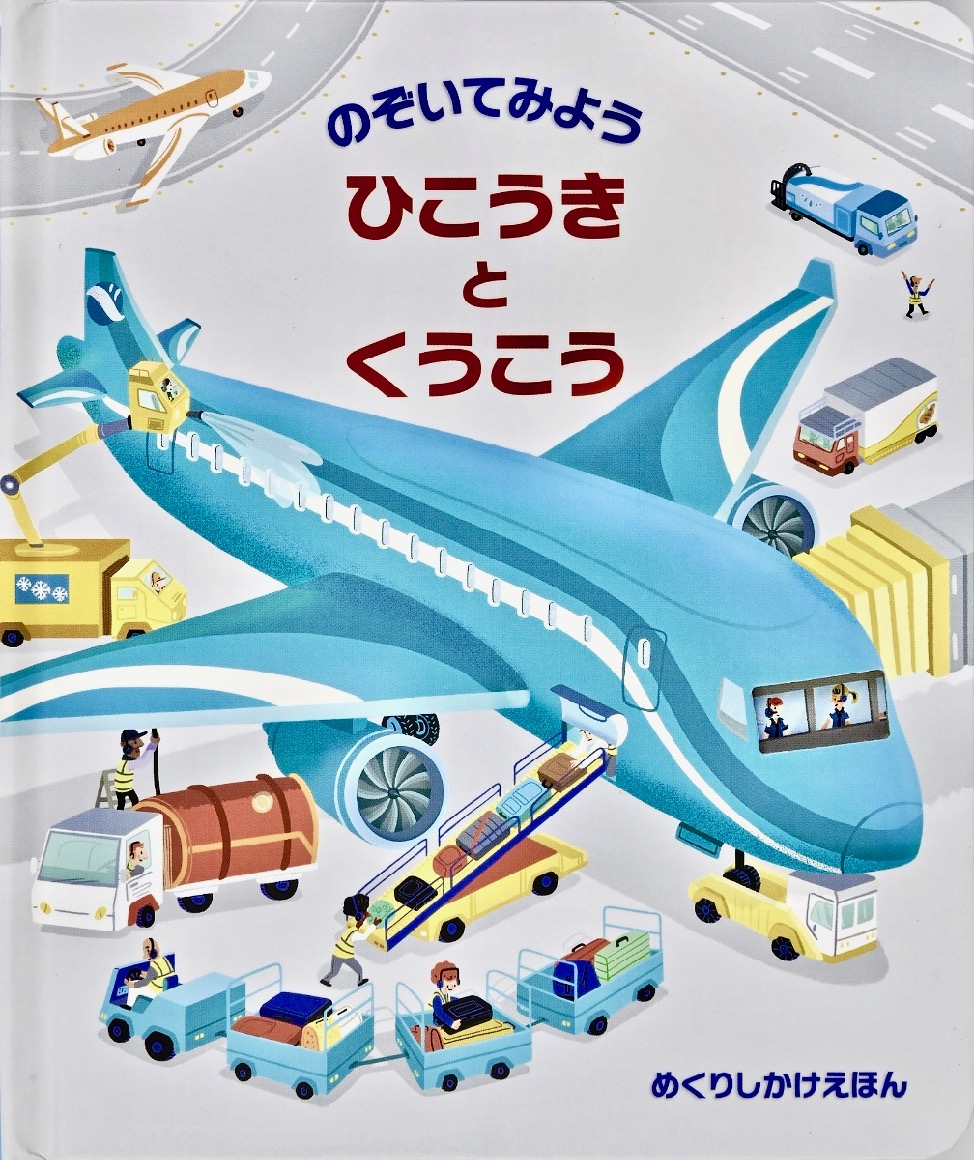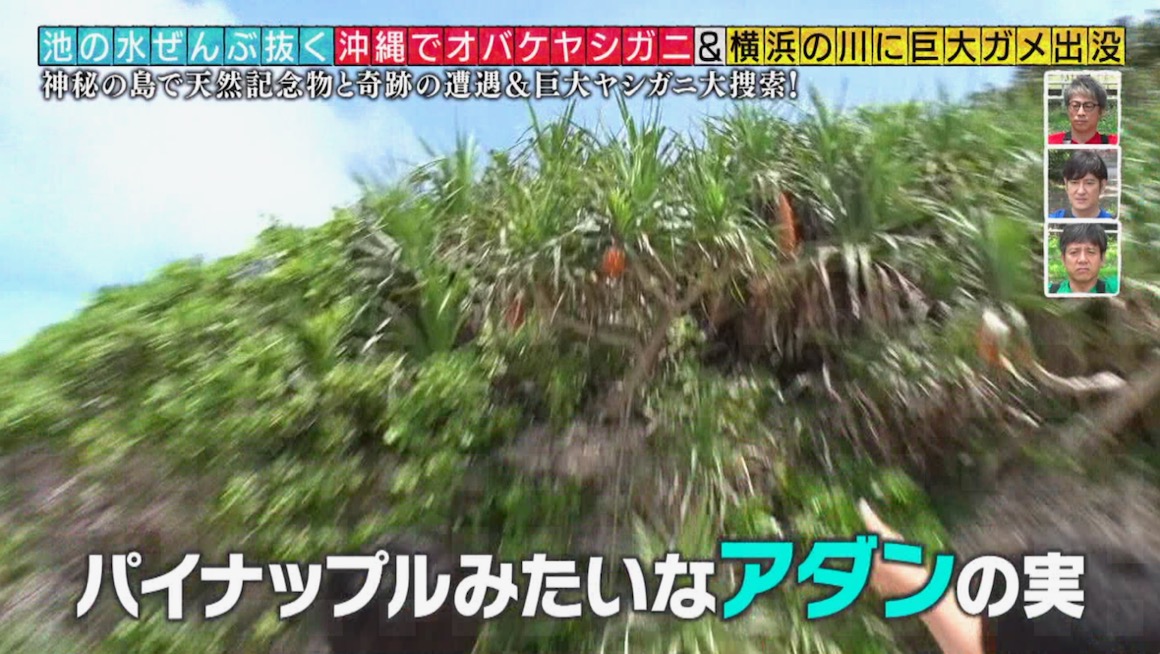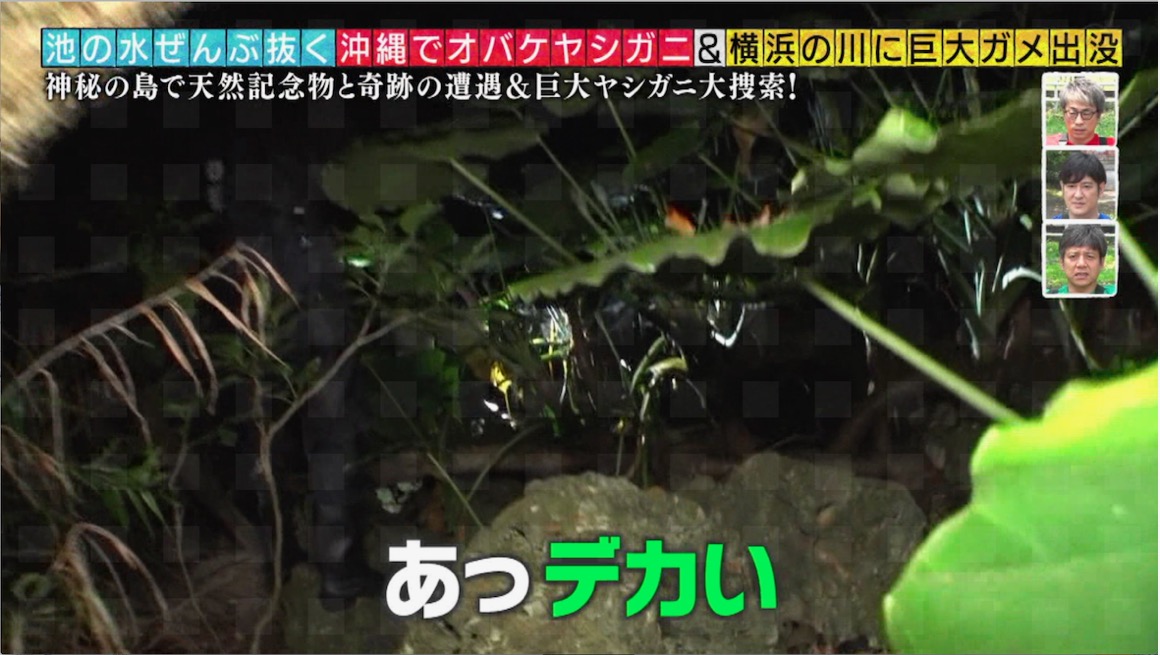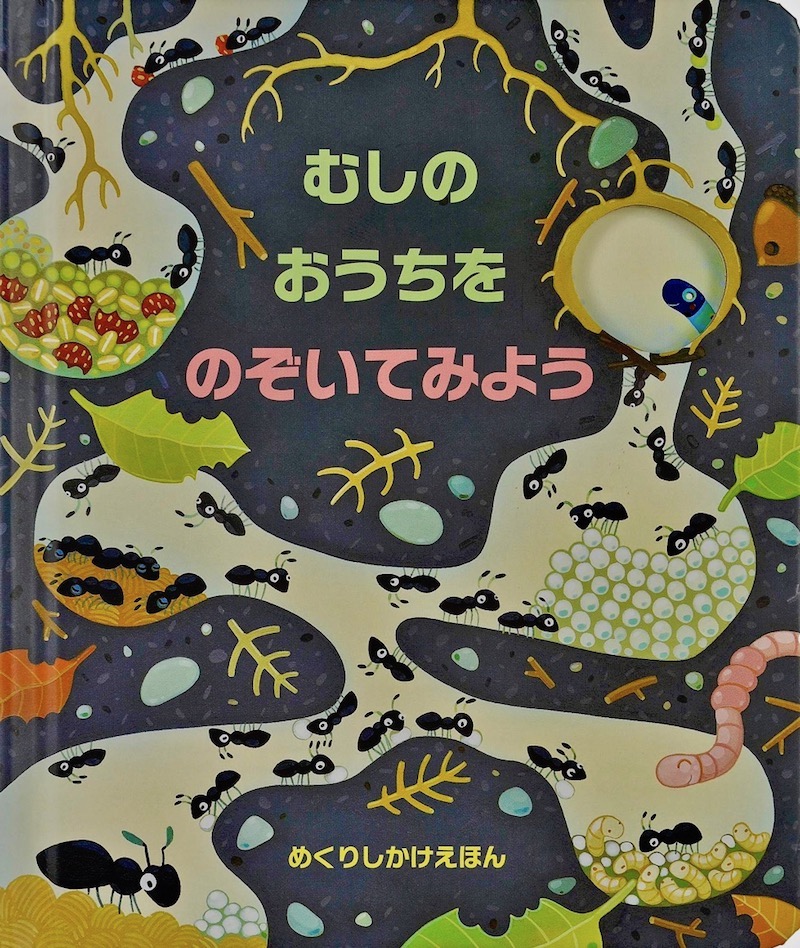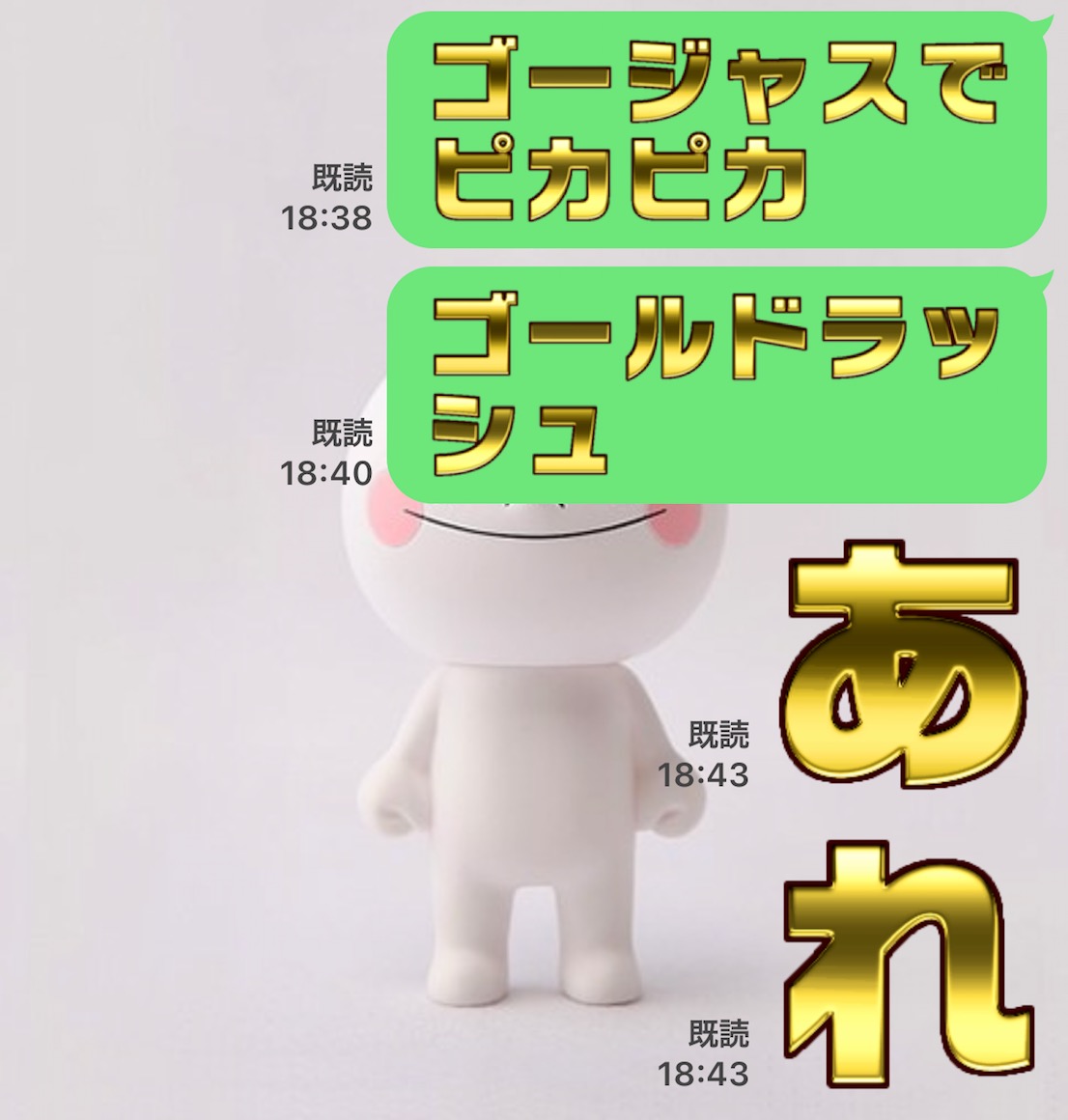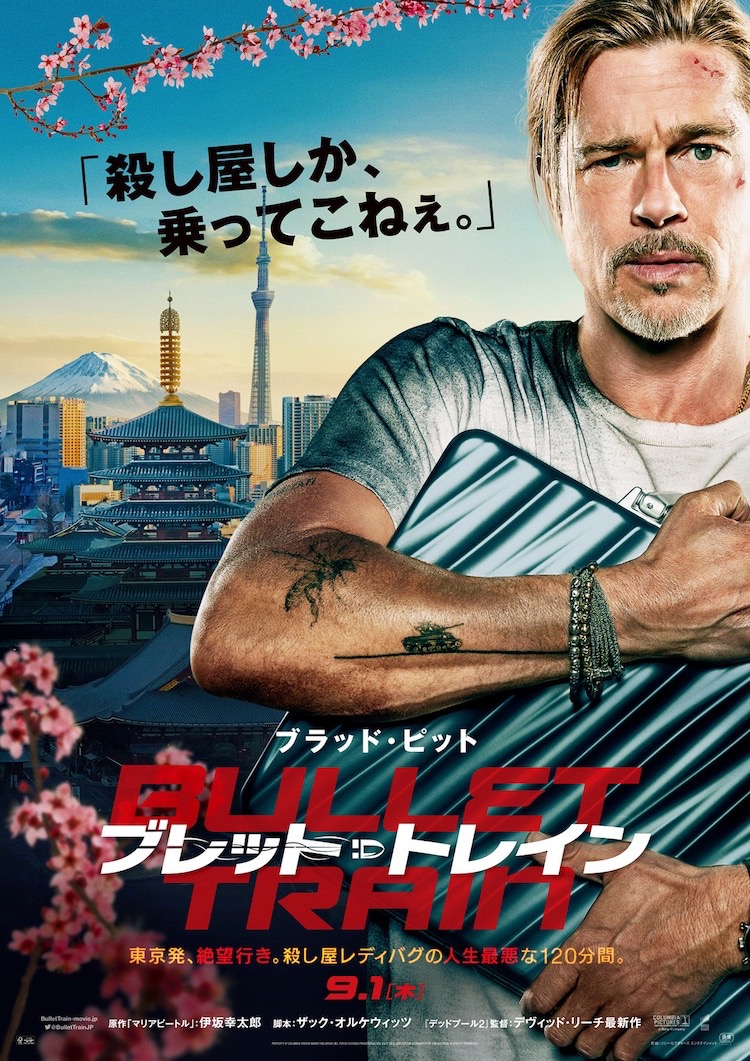
マクドナルドの求人広告画像。
もうひとつ。
チキンタツタとおろしチキンタツタ。
商品パッケージ。
花王株式会社は、お客さまが365日24時間いつでも自分らしく、ごきげんで過ごせる社会を目指し「#ごきげんをつくろう」と称した活動を昨年秋より進めています。
文字色のグラデーションがキレイ…。
まだある。
もうひとつ。
大谷くんが出場する試合は、よく観てる。
こんなのも…。
日本テレビ 世界まる見え!テレビ特捜部
これも…。
まだある。
もうひとつ。
今日から大阪で始まった展覧会、アシタノタイポ展。
サトウY氏の出品作品には、私の書体が使われている。
これがサトウY氏の作品かな。
こんな「ランチパック」もあるんだね。
日本テレビ「秘密のケンミンSHOW極」ランチパックSP。
まだある。
もうひとつ。
明朝体漢字と組み合わせた珍しい例。
書名:道は生きている(新装版)
著者:富山 和子、大庭 賢哉
発行:講談社
これも同じシリーズ。
チャンネル「〇〇の主役は我々だ!」の配信「トンつく」(「トントンと作ろう」の略、トントンはメンバー名)サムネ。